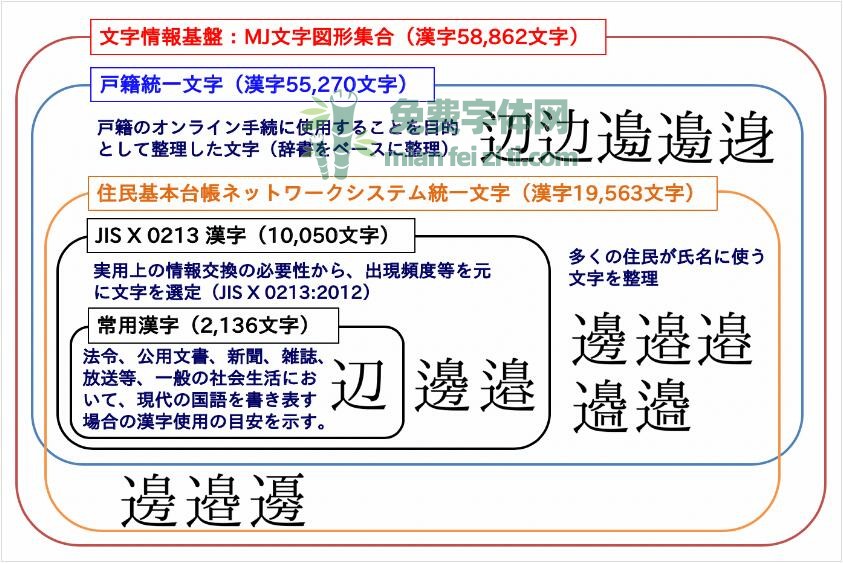
IPAmj明朝体是日本IPA独立行政法人情报处理推进机构推出的一款字体,这是日本的一个关于文字信息基础建设事业的网站。IPA文字信息基础建设事业,是根据日本平成22年电子经济产业省推进计划(关于文字信息基础构建的研究开发事业)启动的,主要是对日本使用的约6万个汉字进行分类整理标准化项目。这个项目公开了《文字信息基础文字一览表》和《IPAmj明朝体》,是为了普及促进和国际标准化的活动。